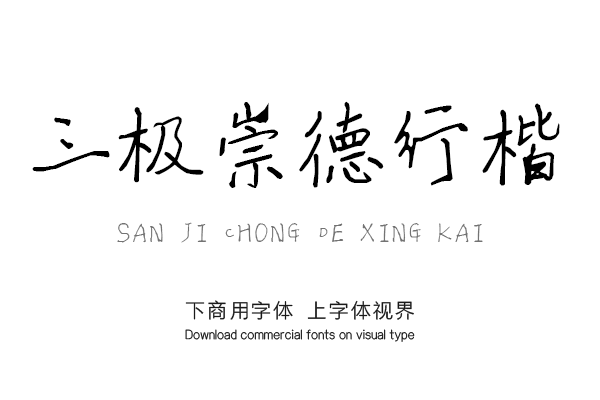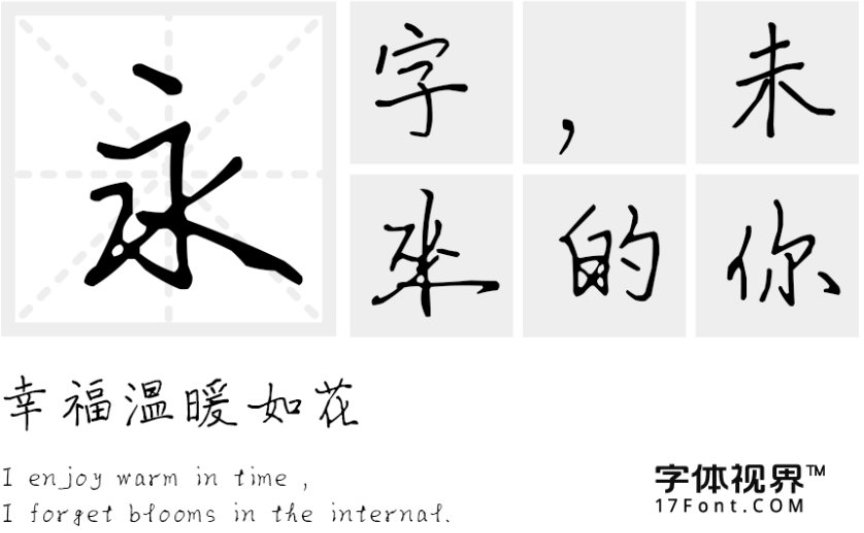
三极崇德行楷|让人赏心悦目,百看不厌的硬笔书法字体
三极崇德行楷发布
字体名称:三极崇德行楷
字体类别: 书法字体、楷体 硬笔字体
适用场景:广告、包装、影视
三极崇德行楷简介:三极崇德行楷,崇明尚德,惟精惟一。严谨秀气而从容淡雅,让人赏心悦目,百看不厌。可广泛用于书刊、广告、包装、影视以及社交网络个性化用字。
三极崇德行楷预览图展示:
三极崇德行楷